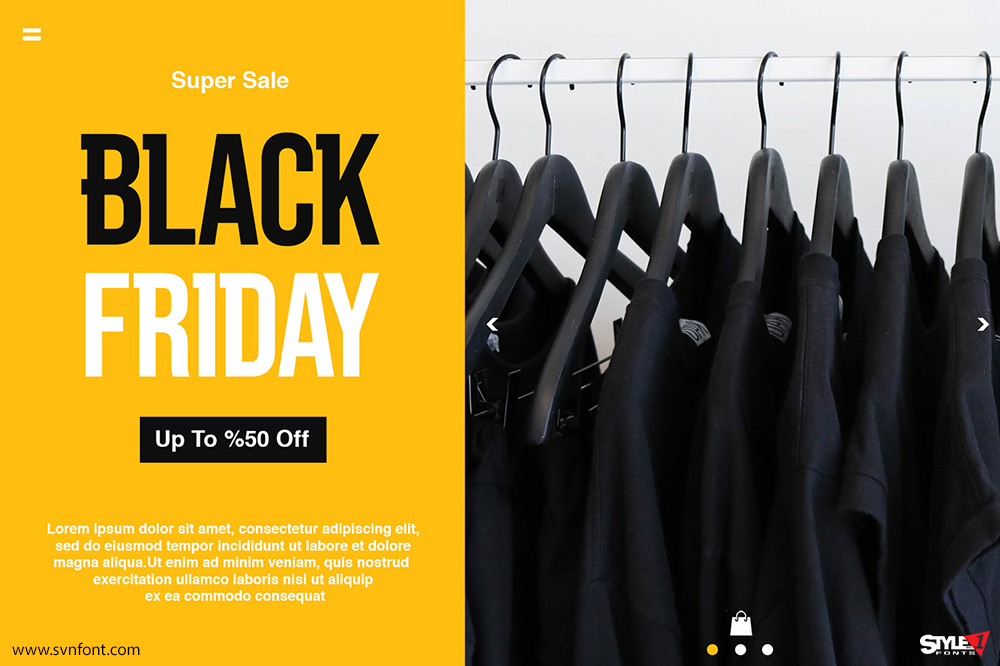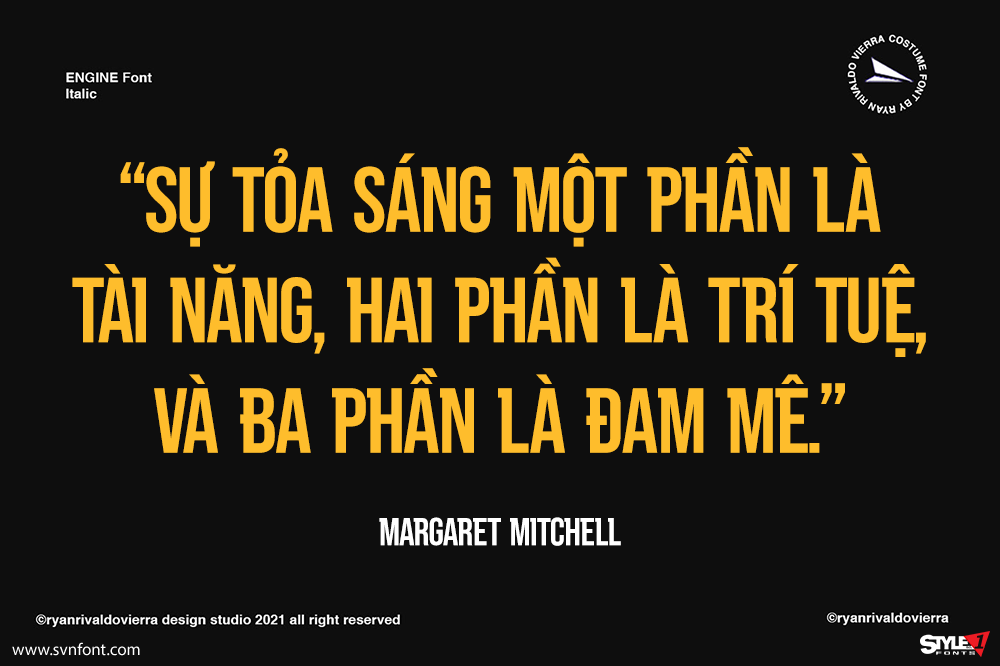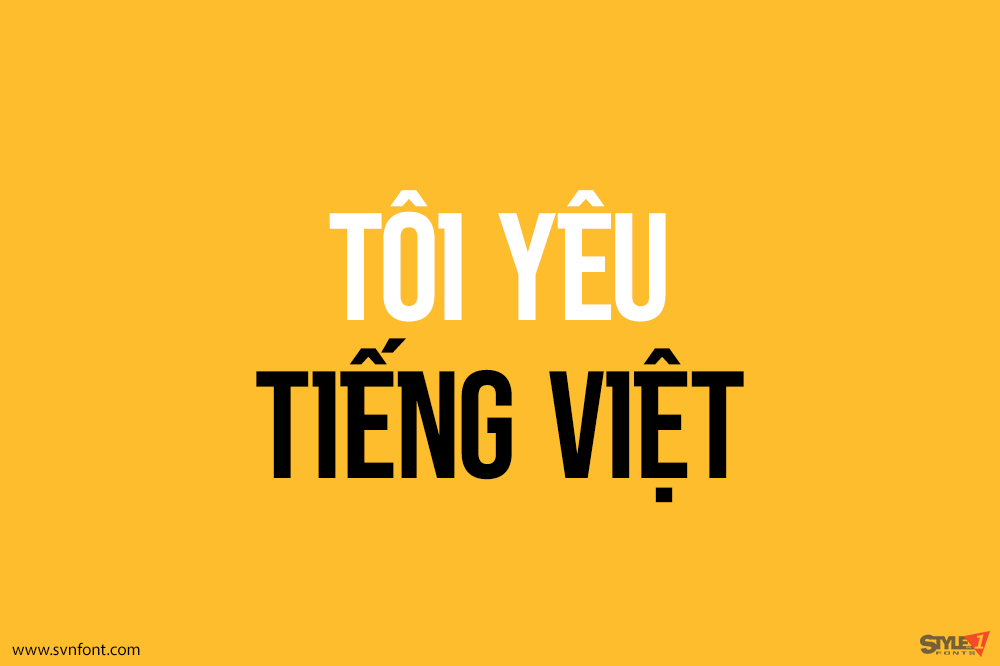
Engine là một font display đậm, được thiết kế chỉn chu để trở thành lựa chọn yêu thích thực thụ. Font sở hữu tiềm năng nâng tầm mọi ý tưởng sáng tạo, giúp thiết kế của bạn trở nên mạnh mẽ, ấn tượng và nổi bật. Font thích hợp cho tiêu đề, logo, banner quảng cáo, in áo cầu thủ…
Nhà thiết kế: Ryan Rivaldo vierra
Nhà phát hành: Ryan Rivaldo vierra